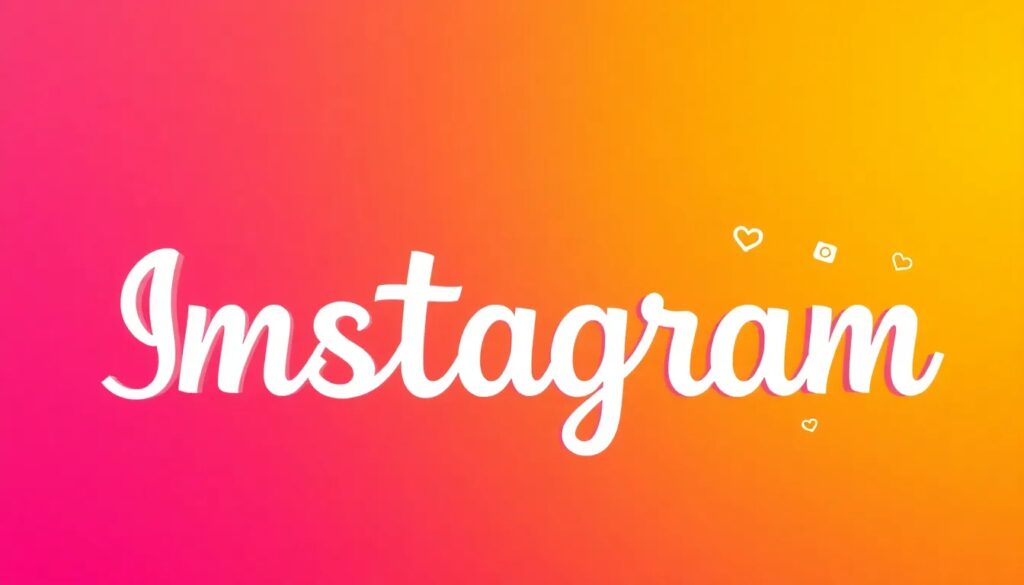
Fonts de instagram: las mejores opciones para tus publicaciones
Las fonts de Instagram son una herramienta vital para quienes desean personalizar y embellecer sus publicaciones en esta popular red social. Gracias a su variedad, puedes adaptar el estilo de tus textos para atraer a más seguidores y mejorar tu presencia online.
En este artículo, exploraremos diferentes aspectos de las fonts de Instagram, desde dónde encontrarlas hasta cómo utilizarlas en tu biografía. Además, nos adentraremos en las fuentes disponibles para Stories y las mejores prácticas para crear una tipografía que resalte tu contenido.
¿Qué son las fonts de Instagram y cómo funcionan?
Las fonts de Instagram son estilos tipográficos que puedes utilizar para personalizar tus publicaciones y perfiles. Estas fuentes permiten que tu contenido destaque en un mar de imágenes y textos monótonos.
El funcionamiento de estas fuentes es bastante sencillo. Puedes utilizar generadores en línea que convierten texto estándar en diferentes estilos tipográficos, todos en formato Unicode. Esto significa que puedes copiar y pegar el texto resultante directamente en Instagram.
Existen diversas aplicaciones, como Glyphy, que ofrecen una amplia gama de opciones. Algunas de las fuentes más populares incluyen contornos, versalitas y estilos burbuja, todos ideales para enriquecer tu contenido visual.
¿Dónde encontrar las mejores fuentes para Instagram?
Encontrar fuentes de letras gratis para Instagram es más fácil de lo que piensas. Aquí te presentamos algunas opciones:
- Glyphy: Una de las plataformas más conocidas para generar fuentes. Ofrece muchos estilos que puedes utilizar en tus publicaciones.
- Lingojam: Este generador de fuentes es fácil de usar y permite crear texto en diferentes estilos rápidamente.
- Cool Symbol: Ofrece una variedad de fuentes y emojis que puedes integrar en tus textos.
- Fancy Text Generator: Ideal para aquellos que buscan letras decorativas y creativas.
Además, muchas de estas herramientas son gratuitas, lo que las convierte en una opción accesible para todos los usuarios de Instagram.
¿Cómo utilizar letras bonitas en tu bio de Instagram?
La biografía de Instagram es uno de los primeros lugares donde los usuarios fijan su atención. Utilizar letras bonitas puede hacer que tu perfil sea más atractivo.
Para añadir estas letras, primero debes generar el texto en un conversor de fuentes. Una vez que tengas el texto estilizado, solo necesitas copiarlo y pegarlo en la sección de tu bio. Así es como puedes añadir un toque único a tu perfil.
Recuerda que la bio tiene un límite de caracteres, así que elige sabiamente qué información incluir. Además, considera combinar letras estilizadas con emojis para hacer tu perfil aún más llamativo.
¿Qué tipos de fuentes están disponibles para Instagram Stories?
Las tipografías Instagram Stories también ofrecen muchas opciones para hacer tus historias más dinámicas. Aquí tienes algunos estilos populares que puedes utilizar:
- Negrita: Ideal para resaltar información clave o mensajes importantes.
- Delgada: Perfecta para un aspecto minimalista y elegante.
- Manuscrita: Aporta un toque personal y auténtico a tus historias.
- Estilo Burbuja: Muy visual y divertido, perfecto para captar la atención.
Además, puedes combinar estos estilos con diferentes colores y fondos para personalizar aún más tu contenido. Las historias son una excelente oportunidad para experimentar y mostrar tu creatividad.
Mejores prácticas para crear fuentes personalizadas en Instagram
Crear fuentes personalizadas en Instagram es un arte que puede aumentar tu engagement. Aquí hay algunas mejores prácticas para considerar:
- Consistencia: Mantén un estilo tipográfico coherente en todas tus publicaciones para que tu marca sea reconocible.
- Legibilidad: Asegúrate de que el texto sea fácil de leer, incluso en dispositivos móviles. Fuentes demasiado elaboradas pueden dificultar la lectura.
- Combina colores y estilos: No dudes en mezclar diferentes colores y estilos tipográficos para darle vida a tus publicaciones, pero asegúrate de que todo fluya bien.
- Utiliza espacio: No sobrecargues tus imágenes con texto. A veces, menos es más, y un diseño limpio puede ser más efectivo.
Estas estrategias pueden ayudar a que tu contenido sea más atractivo y, por ende, incrementar la interacción con tus seguidores.
¿Cómo copiar y pegar fonts de Instagram?
El proceso de copiar y pegar fonts de Instagram es bastante simple, pero aquí te explicamos cómo hacerlo paso a paso:
1. Elige un generador de fuentes: Visita una de las herramientas mencionadas anteriormente, como Glyphy o Lingojam.
2. Escribe tu texto: Introduce el texto que deseas estilizar en la caja de texto del generador.
3. Selecciona la fuente: Escoge el estilo que más te guste de la lista de fuentes generadas.
4. Copia el texto: Una vez que hayas elegido la fuente, copia el texto estilizado que aparece.
5. Pega en Instagram: Dirígete a la aplicación de Instagram y pega el texto en el lugar deseado, ya sea en tu publicación, historia o bio.
Este proceso te permitirá personalizar tus textos de manera rápida y efectiva, haciendo que tus publicaciones se destaquen.
Este video te mostrará algunas de las mejores herramientas y consejos para utilizar fuentes de Instagram de manera efectiva. Asegúrate de verlo para descubrir aún más maneras de mejorar tus publicaciones.
Conclusión: potencia tu presencia en Instagram con las fuentes adecuadas
Utilizar las fonts de Instagram correctas puede marcar la diferencia en la manera en que tus publicaciones son percibidas. Elegir tipografías que reflejen tu personalidad y estilo no solo hará que tu contenido sea más atractivo, sino que también puede incrementar tu engagement y seguidores.
Desde mejorar la estética de tu perfil hasta facilitar la comunicación visual con tus seguidores, las fuentes son una herramienta poderosa en el mundo de las redes sociales. Así que no dudes en experimentar y adaptar tu estilo con diferentes fuentes y emojis, haciendo de tu contenido algo único y memorable.